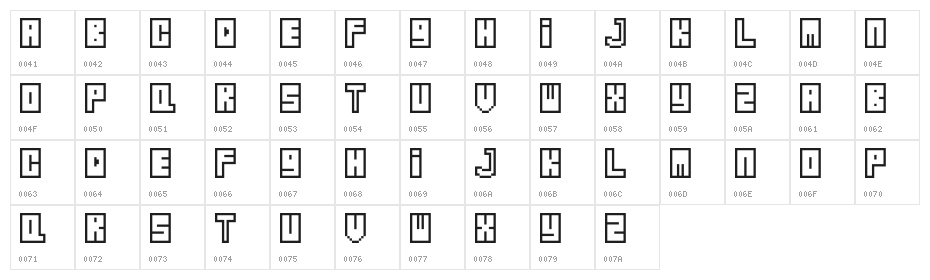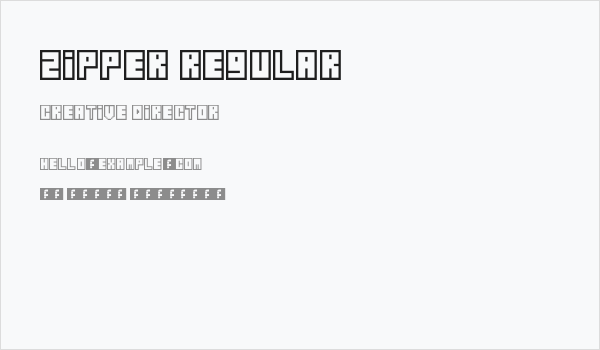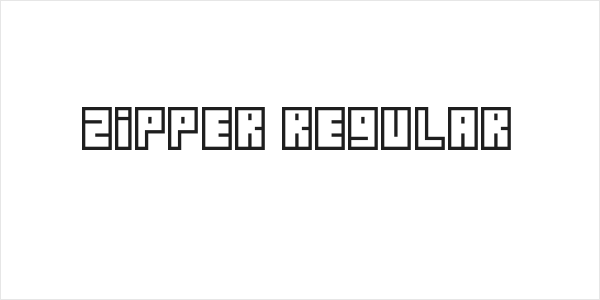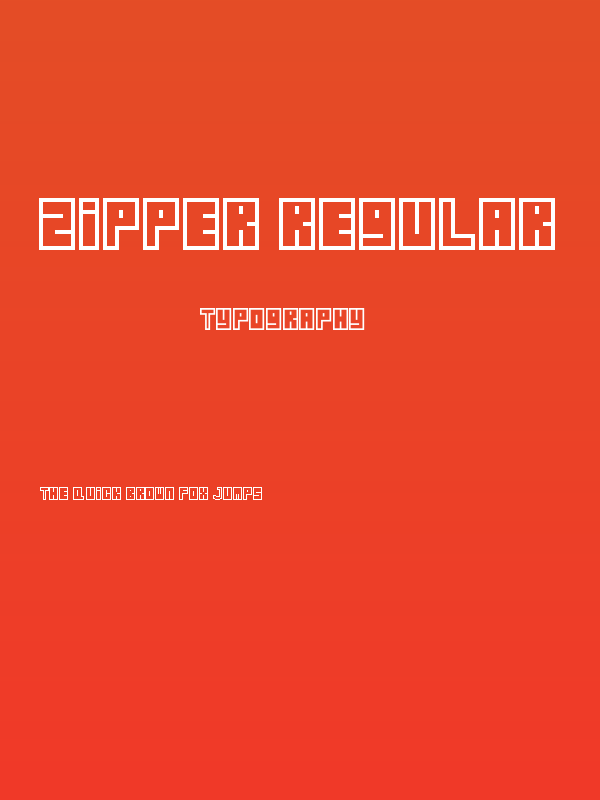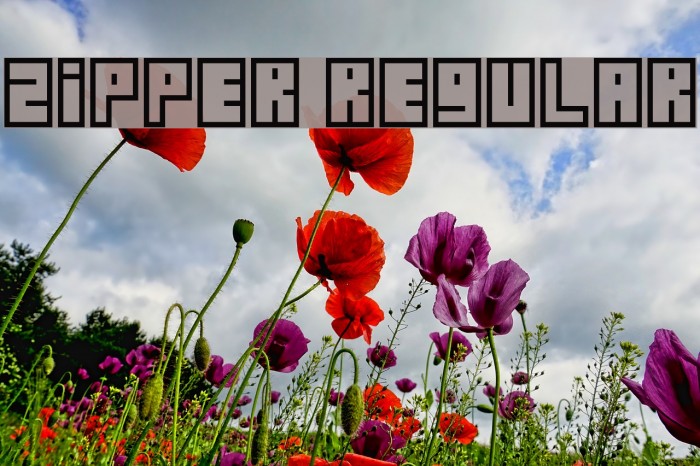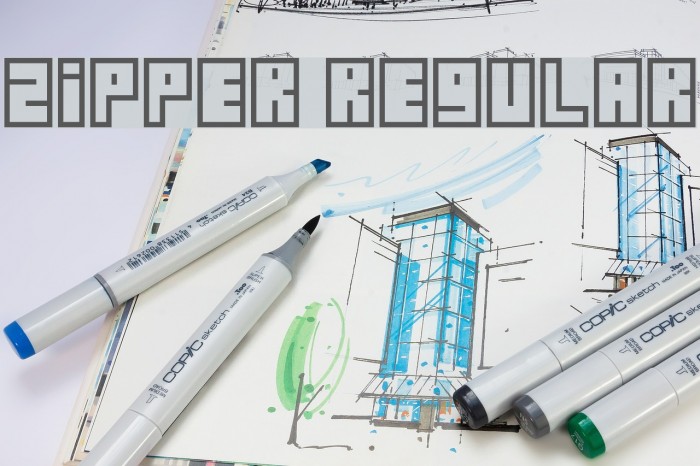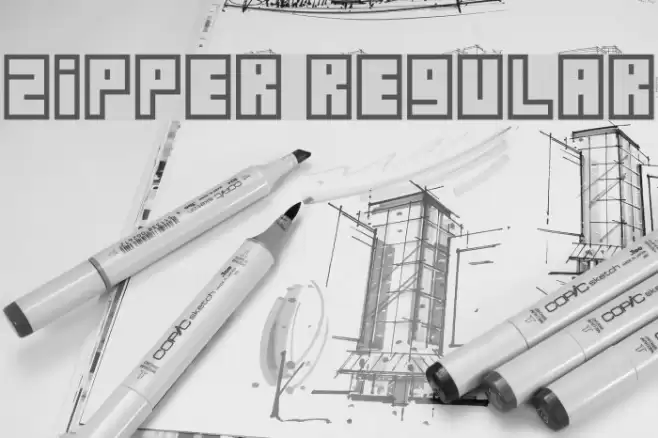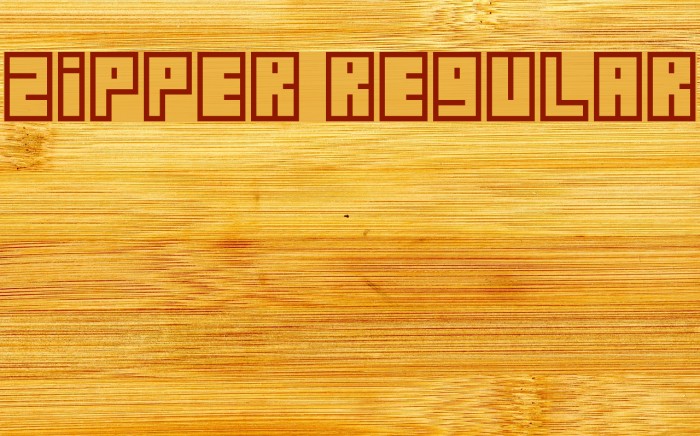
Zipper Regular Font
| श्रेणियाँ | Pixel |
| समग्र शैली | Retro, Digital |
| उपयोग का मामला | Logos, Headlines, Posters |
| सुझाए गए प्रोजेक्ट | Ideal for video game graphics, tech-themed posters, digital art, and retro-style branding. |